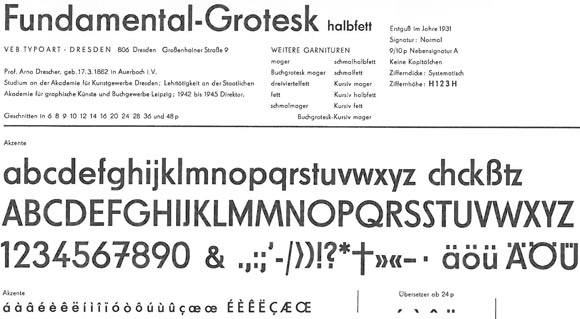
Letraset … wer erinnert sich noch?
Na, und ob ich mich noch erinnere. Dynamo und Frankfurter
waren unsere Favoriten bei der Plakatgestaltung. Mein Gott, wie
lange ist das schon wieder her...
… Typofix! …
Mann, ich habe mir gestern das Hirn zermartert nach diesem Wort, es ist mir einfach nicht eingefallen. Hatten die Dinger in der DDR eigentlich auch Relevanz in der Druckformenherstellung? Ich kenne das nur als Bastelartikel.
Ich bin ja schon eine andere Generation :-D
... aber kennt ihr noch diese Omnichrom-Geschichte (war, glaube ich auch von Letraset), das wünschte ich mir ja manchmal noch zum Dummybauen :-(
Sieh an, die gute alte Fundamental-Grotesk von Arno Drescher...
Hatte Typoart die eigentlich auch als Bleisatzschrift im Angebot?
Na klar. In mindestens zehn Schnitten.
Aus eigener Anwendung kenne ich Letraset nicht mehr, aber in der ersten Designagentur, in der ich ein Praktikum gemacht habe, gab es noch etliche Kästen mit Letraset-Material, die in einer ungenutzten Ecke des Archivs ihre letzte Ruhe gefunden hatten – und die ich bei der Neuordnung des Archivs (> klassischer Praktikantenjob) wiederentdeckte. :-)
Ich kenne aber noch »Chromatecs« (das Verfahren gibt es sicherlich unverändert), das sind auch so Rubbelbögen, auf die wir für den Dummybau alle Schrift- und Bildelemente drucken ließen, um sie dann später in nervenaufreibender Fummelarbeit auf die Dummies zu übertragen. Und bei manchen Wetterlagen hat der Mist einfach nicht kleben wollen … :neenee:
typofix oder jürafix , der vorgänger? (hab mal irgendwo gelesen das dieser name
vom 'erfinder/hersteller' jürgen ra... stammt. danach wurde die firma verstaatlicht
und es wurde typofix daraus) hab ich auch noch 'nen packen hier liegen.
maxima, folio, fundamental grotesk und englische schreibschrift.
in der druckvorstufe wurde es glaube weniger genutzt, eher zum beschriften von dingen
oder zur gestaltung von wandzeitungen. auch bei der leiterplattenherstellung und NVA
kamen die buchstaben und taktischenzeichen oft zum einsatz.
Ralf Herrmann schrieb:
Bei uns hieß das Typofix! :-)
Toll, danke! Eine Zeit lang war das in meiner Schulklasse eine richtige Manie und wir haben alles mögliche mit den Buchstaben verziert.